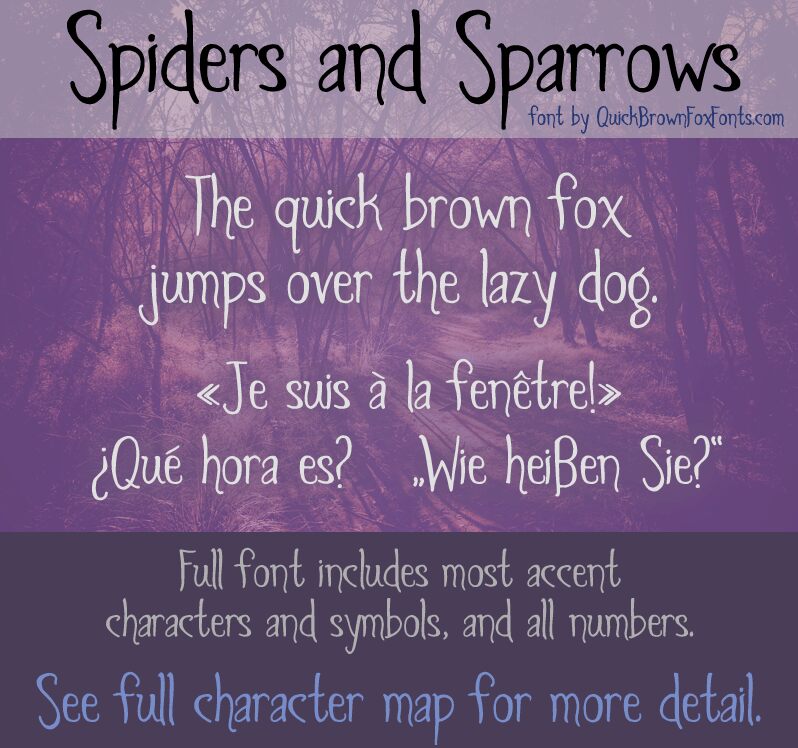
Spiders and Sparrows ist eine verspielte, schelmische, leicht gotische und etwas unheimliche Schrift. Sie wirkt in Titelschreibweise, komplett in Großbuchstaben oder in Kleinschreibung. In kleineren Größen kommt der unheimliche Charakter noch besser zur Geltung.
Spiders and Sparrows DEMO